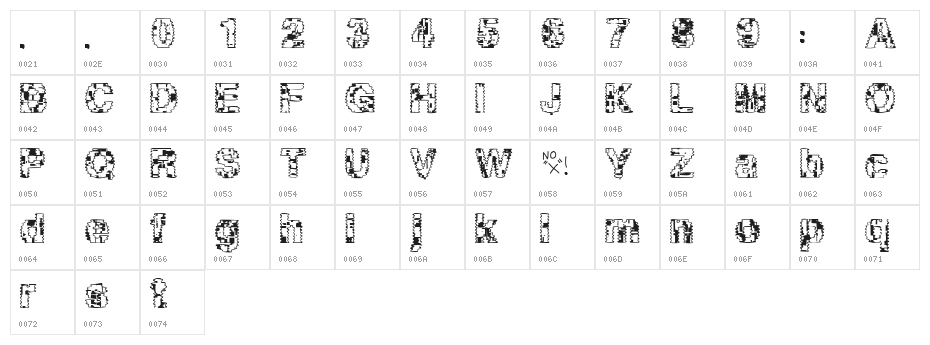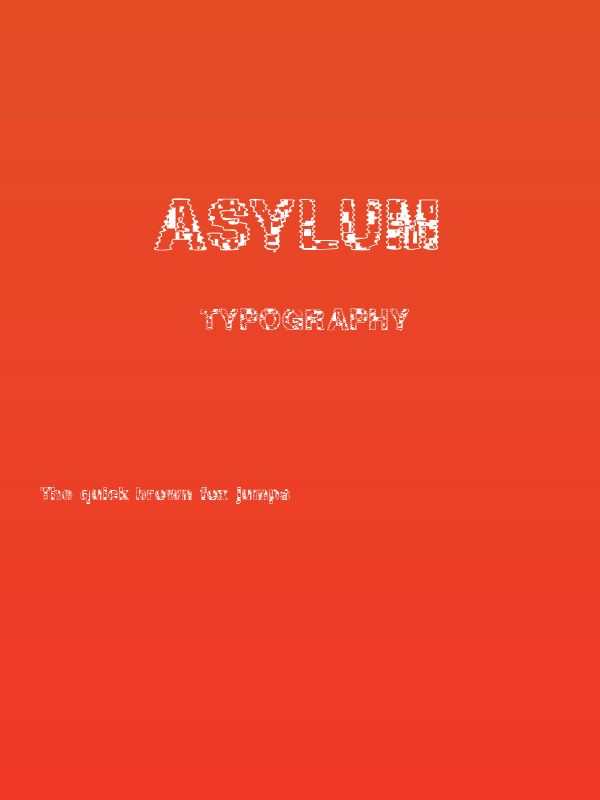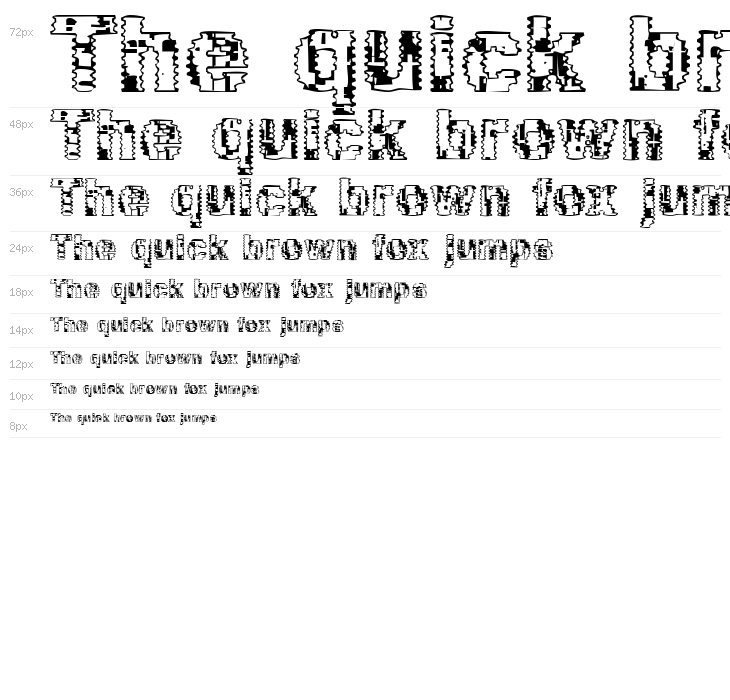
Asylum Font
| Gesamtstil | Grunge, Edgy, Distressed |
| Anwendungsfall | Headlines, Posters, Creative Designs |
| Vorgeschlagene Projekte | Ideal for music album covers, edgy posters, and creative designs seeking a bold impact. |